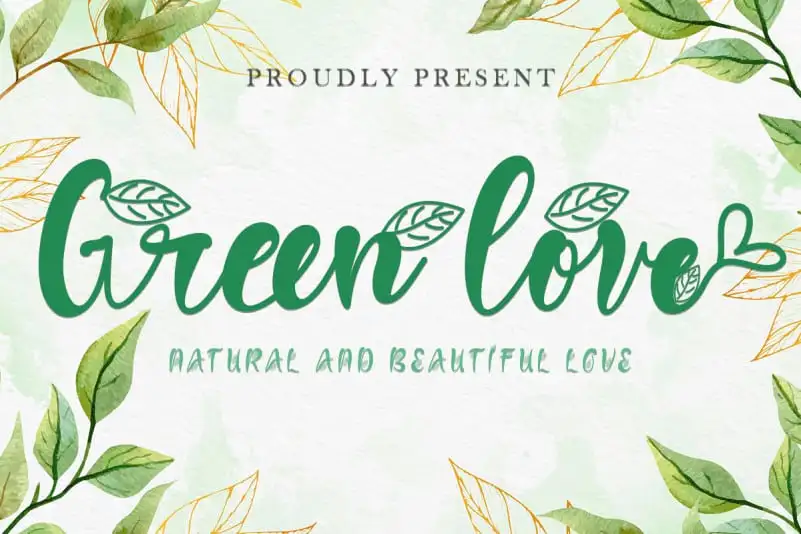
Green Love Script Font – Download Grátis
A “Green Love Script Font” é uma elegante tipografia de calligrafia com caracteres que dançam perfeitamente ao longo do nível de base. Esta fonte PUA (Propriedades Unicode Avançadas) permite que você acesse facilmente todos os gílitos e swashes, adicionando um toque romântico e suave à sua designação ou projeto. Este estilo elegante é perfeito para adicionar personalidade ao seu trabalho gráfico, seja em cartazes publicitários, editoriais de revistas ou até mesmo na criação de logotipos. Com a “Green Love Script Font”, você pode criar mensagens suaves e apaixonadas sem precisar sair da sua mesa de trabalho.